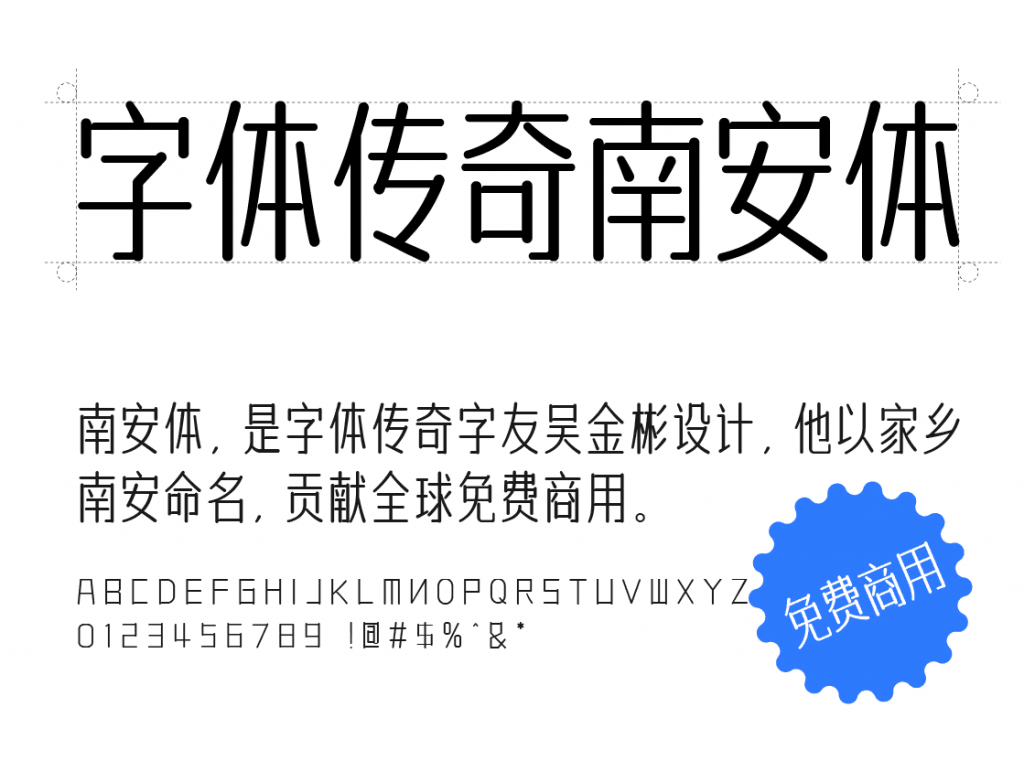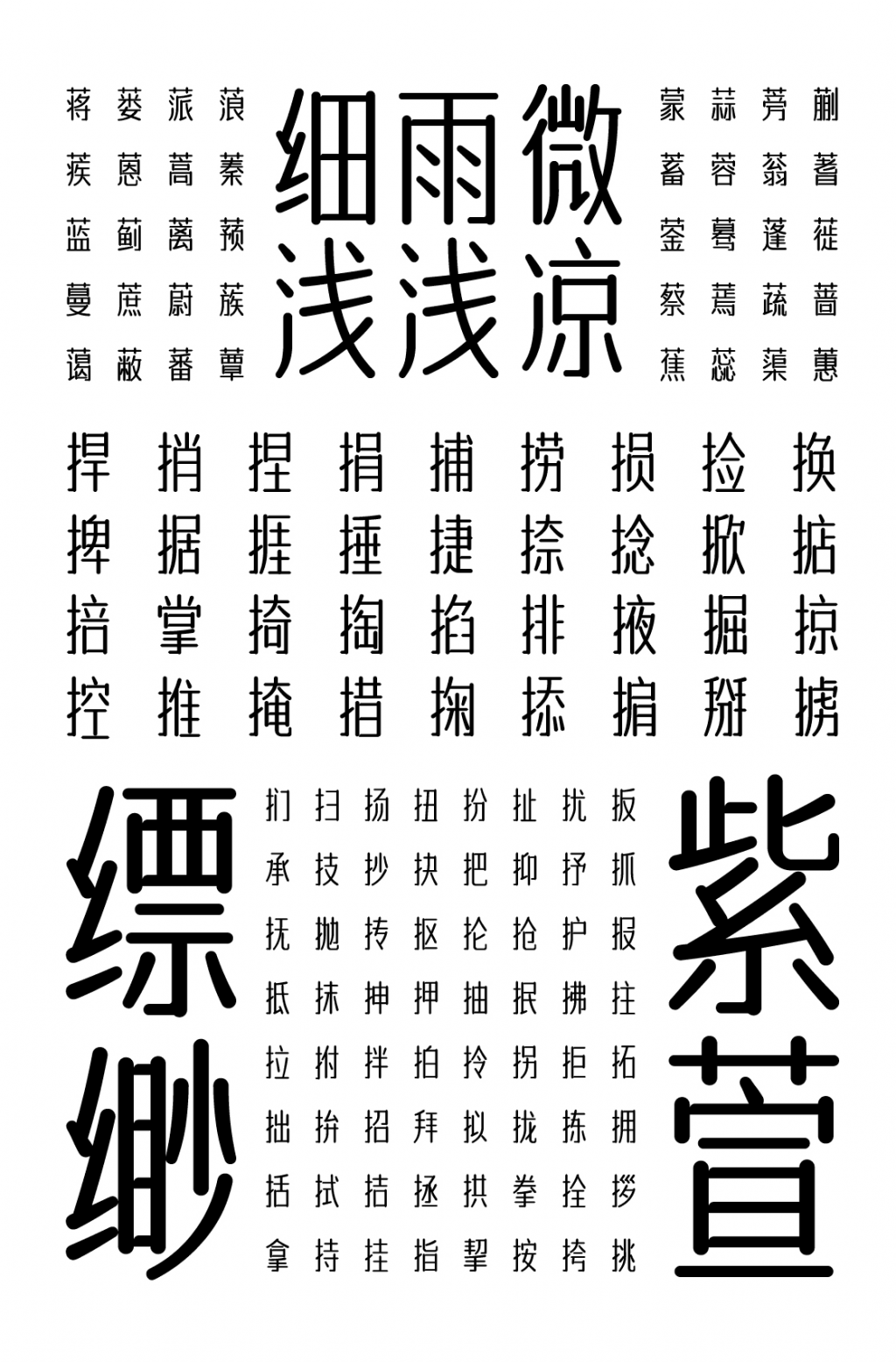
字体传奇南安体是字体传奇网字友吴金彬设计字体传奇编码完成的一套免费商用字体,字体的起名是吴金彬以他的家乡南安命名的,他把这款字体,贡献给大家永久免费商用,也希望大家记住吴金彬和他的家乡南安。
吴金彬言:我一直在寻找一个可以干到老的工种,毕竟人总是会老的种田我又不会,兜兜转转N年后发现字库这行当非常符合我的需求,所以盲目的就开始了做字库之旅因为我是个干维修工作的对于设计这块一知半解也没有过培训啥的,跨界跨得有点狠当字库做到800多字的时候,好几次都想放弃不伺候了因为不舍得最后想也想通了,自己挖的坑含着泪也要把它填平了总不会要把初心扔进坑里吧!直到初稿完成后又出现各种问题,光来来回回的修改花了近初稿时间的3倍。整个过程没法细说只能风干了当下酒菜…
“字体传奇南安体-免费商用”是一款书写很新颖的字体,字体大方,适合各种设计作品使用!欢迎下载!